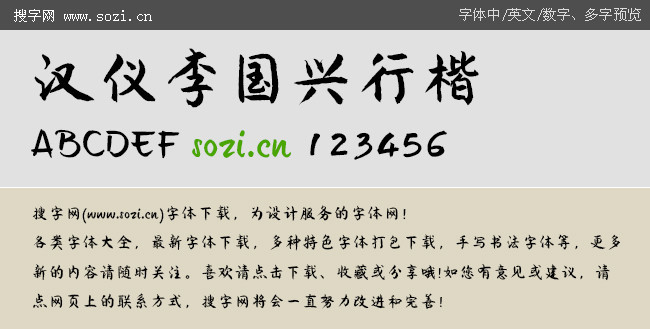
漢儀李國興行楷
搜字網(wǎng)給大家提供一款漢儀李國興行楷中文字體下載,漢儀李國興行楷筆畫行如流水,單個字體大小一致,整體效果十分整齊優(yōu)美,適合應(yīng)用于藝術(shù)設(shè)計、平面宣傳設(shè)計、網(wǎng)頁設(shè)計等應(yīng)用。(本字體為個人非商用版,如需要商用請聯(lián)系漢儀公司購買版權(quán))